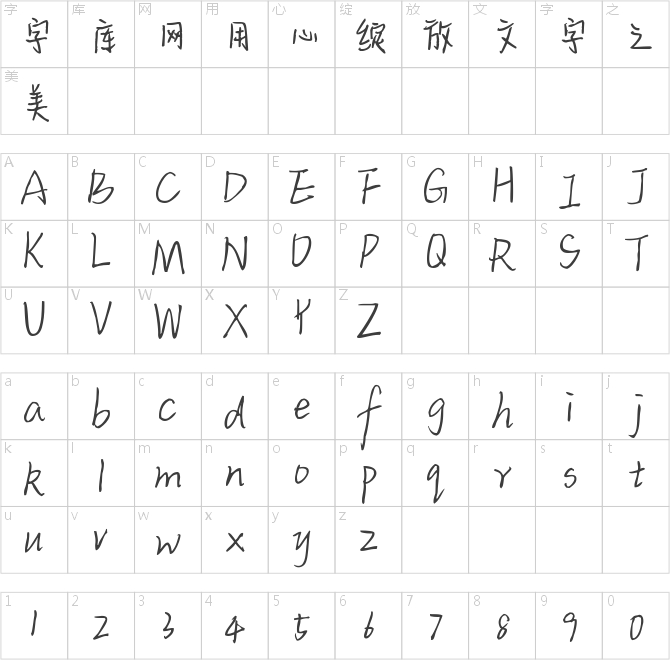
字樂(lè)對(duì)你的愛(ài)
字樂(lè)對(duì)你的愛(ài)字體字庫(kù)是一款讓人賞心悅目、百看不厭的中文字體,適合各類廣告和產(chǎn)品包裝設(shè)計(jì)應(yīng)用,字體大小7.33MB,格式為ttf字體,上傳用戶是神經(jīng)蛙6,作者/版權(quán)方為字體圈